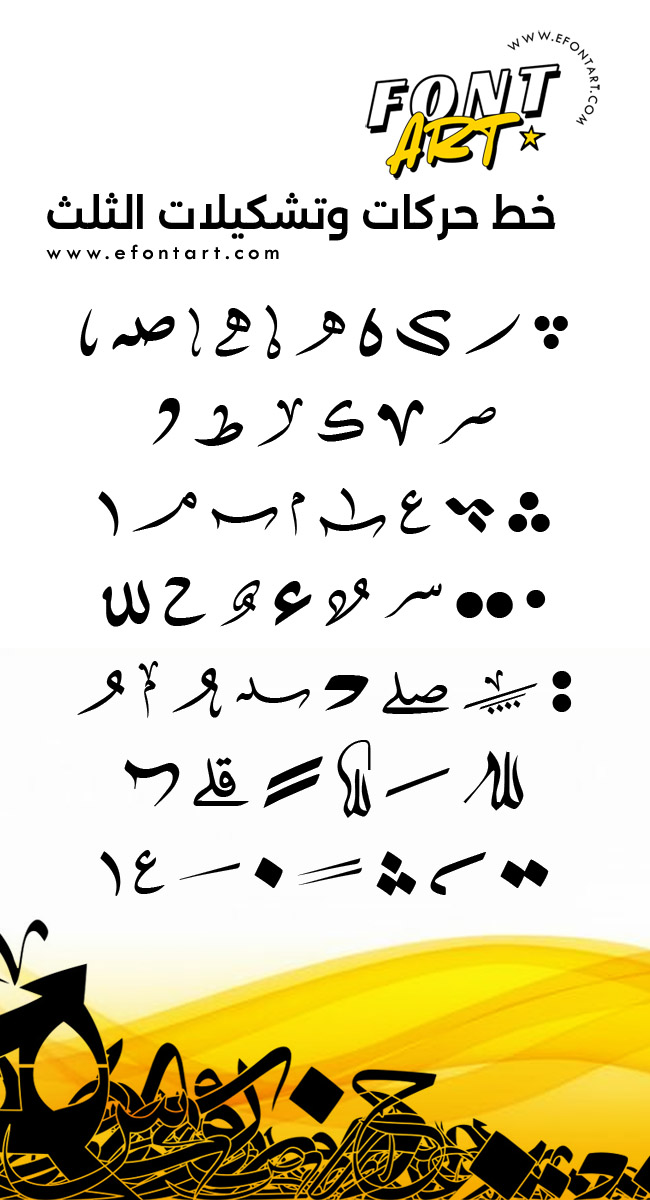
خط حركات وتشكيلات الثلث .. خط الحركات النحوية والذي يحتوي على أجمل التشكيلات الخاصة بخط الثلث العريق ، هذه التشكيلات الخفيفة تضفي إلى موضوعك أو تصميمك لمسة جمالية رقيقة ، ويمكن استخدامه في برامج الأوفيس وبرامج التصميم المتنوعة ، كما أنه يعمل بالحروف الإنجليزية كابيتال وسمول ، ومتاح للتحميل المجاني .
خط حركات وتشكيلات الثلث